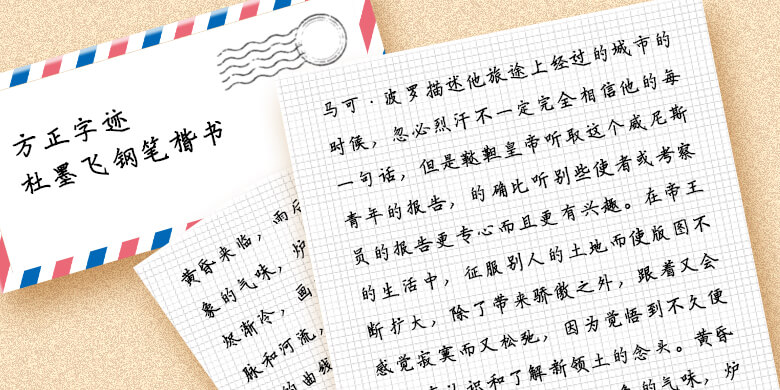
方正字迹-杜墨飞钢笔楷书-简繁
作者杜雄侠,艺名杜墨飞,其“杜墨飞钢笔楷书”取法晋唐诸家,从临摹欧阳询、柳公权、颜真卿、赵孟頫“楷书四家”作品中吸取营养,架构综合了颜体的宽博端整,疏密停匀,欧体的秀骨清神,中宫紧聚,赵体的空灵圆融,结体严整。在笔法上,笔画起笔,折笔多以赵体为宗,竖画,点法得欧体神韵。钩法,撇画多学颜体取势。经过多年磨砺,逐渐形成自己独特的硬笔书法风格。
“杜墨飞钢笔楷书”字体有幸做成方正字库,使之得以更加广泛的传播,服务社会大众。字体严谨而富于变化,遒丽典雅,结体周密;行笔劲健酣畅,精致秀美,是钢笔楷书学习的典范,并可广泛应用于现代互联网信息平台,是qq、微信等社交平台理想的个性首选字体。